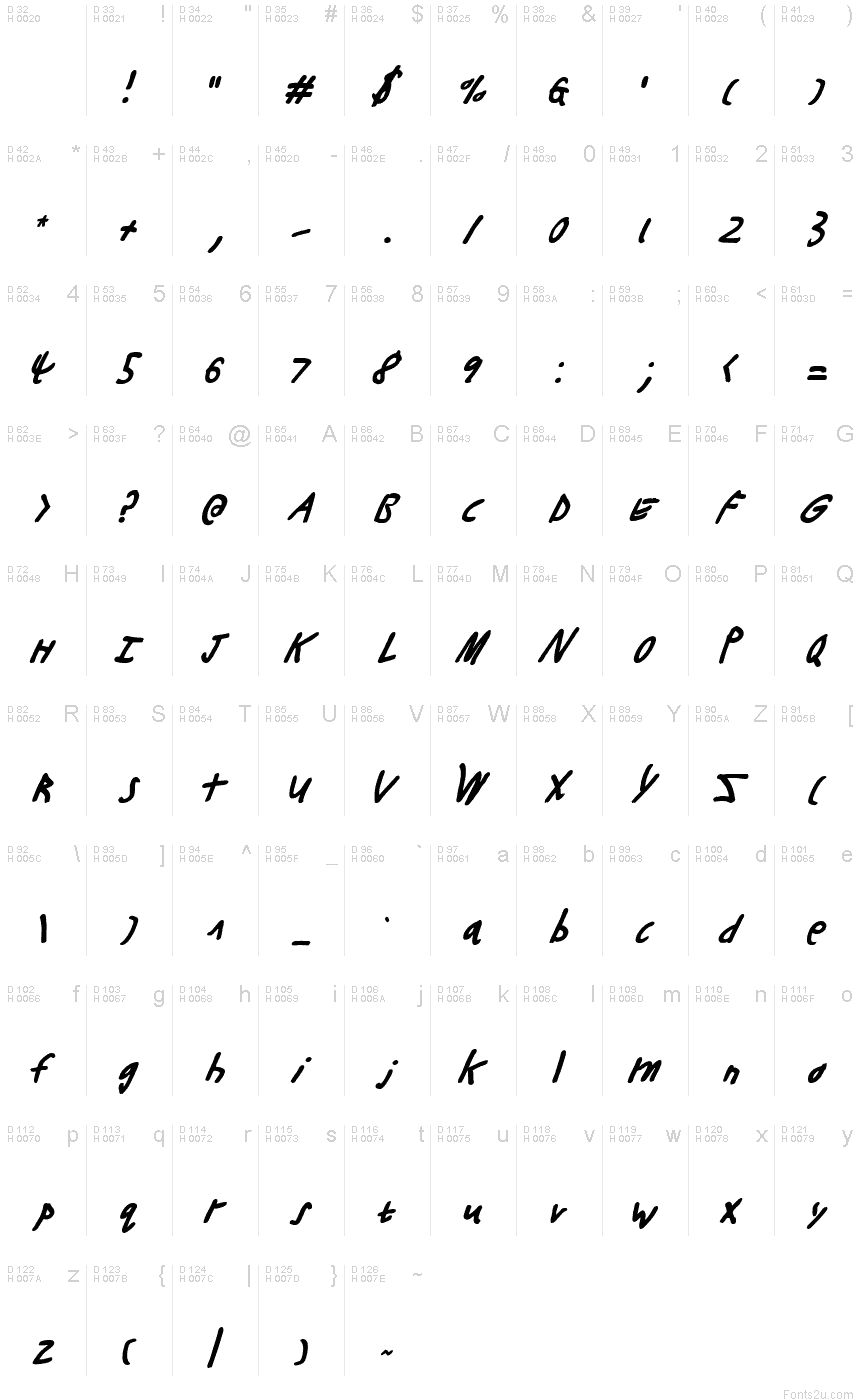
Buttons the Bear Italic od Iconian Fonts to darmowy krój pismowy w stylu pędzla, charakteryzujący się wyrazistym, dynamicznym rytmem. Jego szerokie pociągnięcia, miękkie łuki i energiczne nachylenie w prawo przywodzą na myśl odręczny napis grubym markerem, a nieregularne kształty nadają mu ciepły, swobodny charakter.
Ta odręczna energia idealnie pasuje do okładek książek dla dzieci czy opakowań zabawek, a także wniesie radosny ton do zaproszeń urodzinowych czy plakatów szkolnych. Jako darmowy font naturalnie sprawdza się również w zabawnej grafice gier oraz w rzemieślniczym brandingu, ponieważ jego mocne kształty śmiało komponują się z pogodnymi ilustracjami.
Buttons the Bear Italic